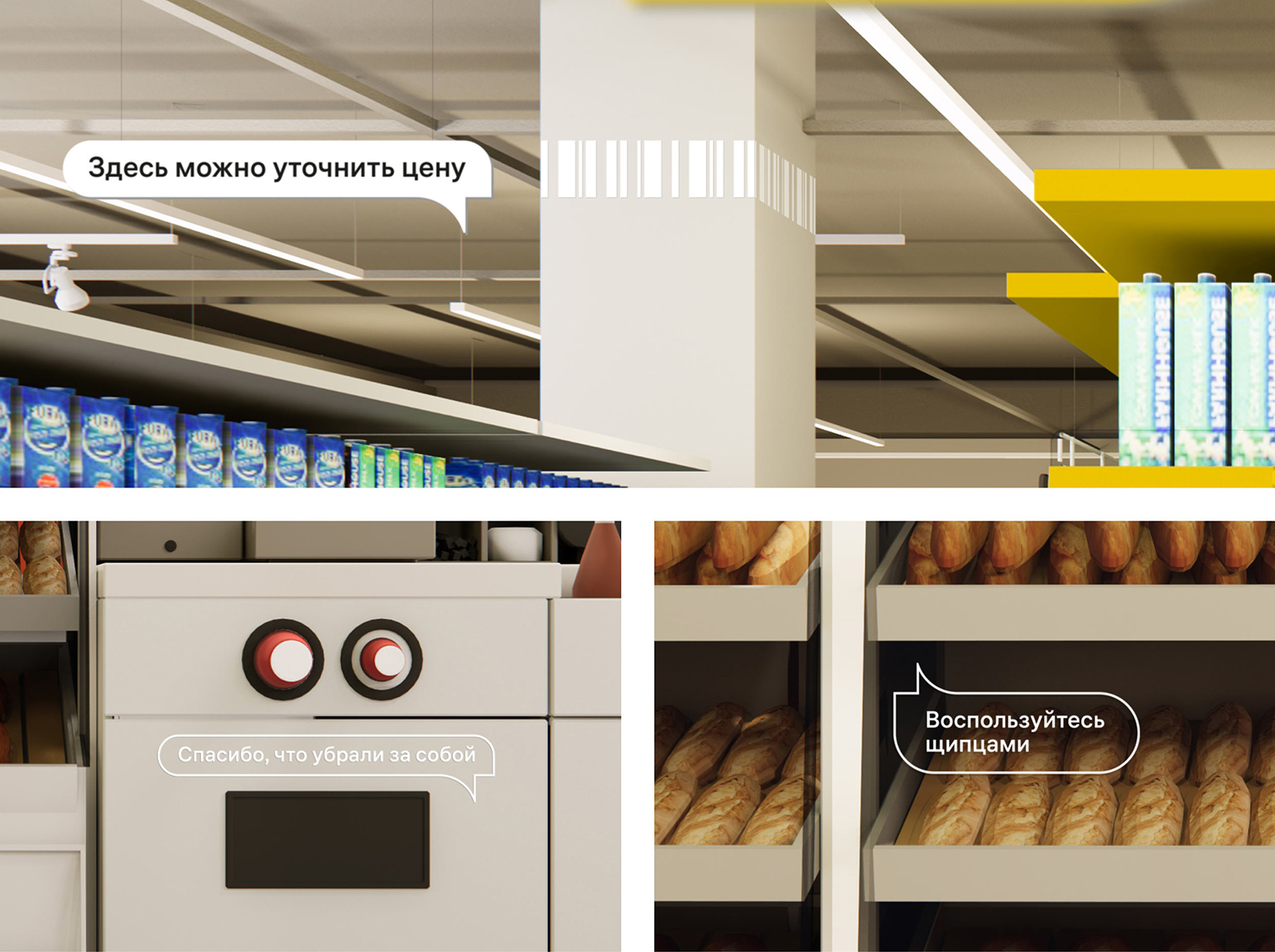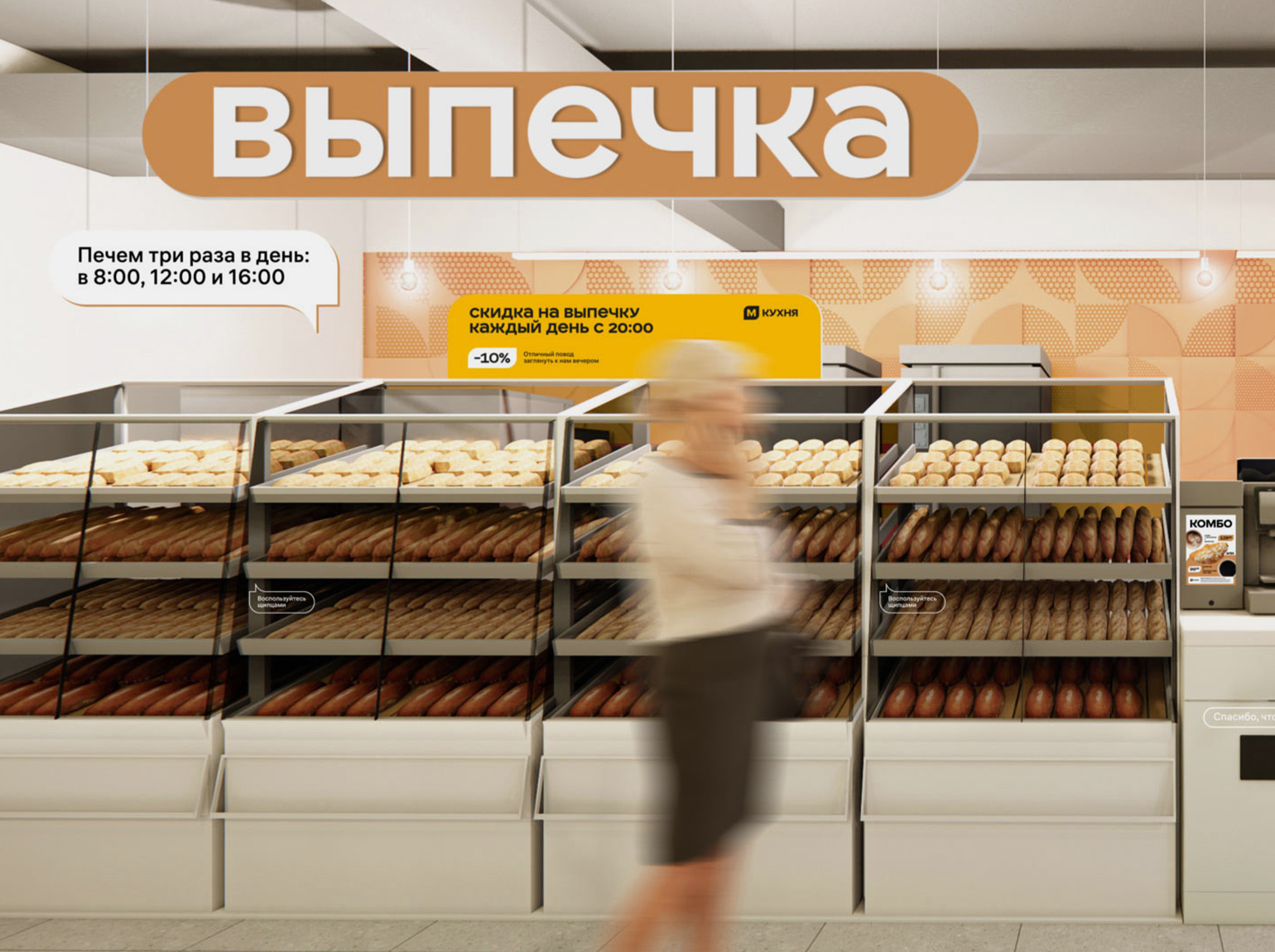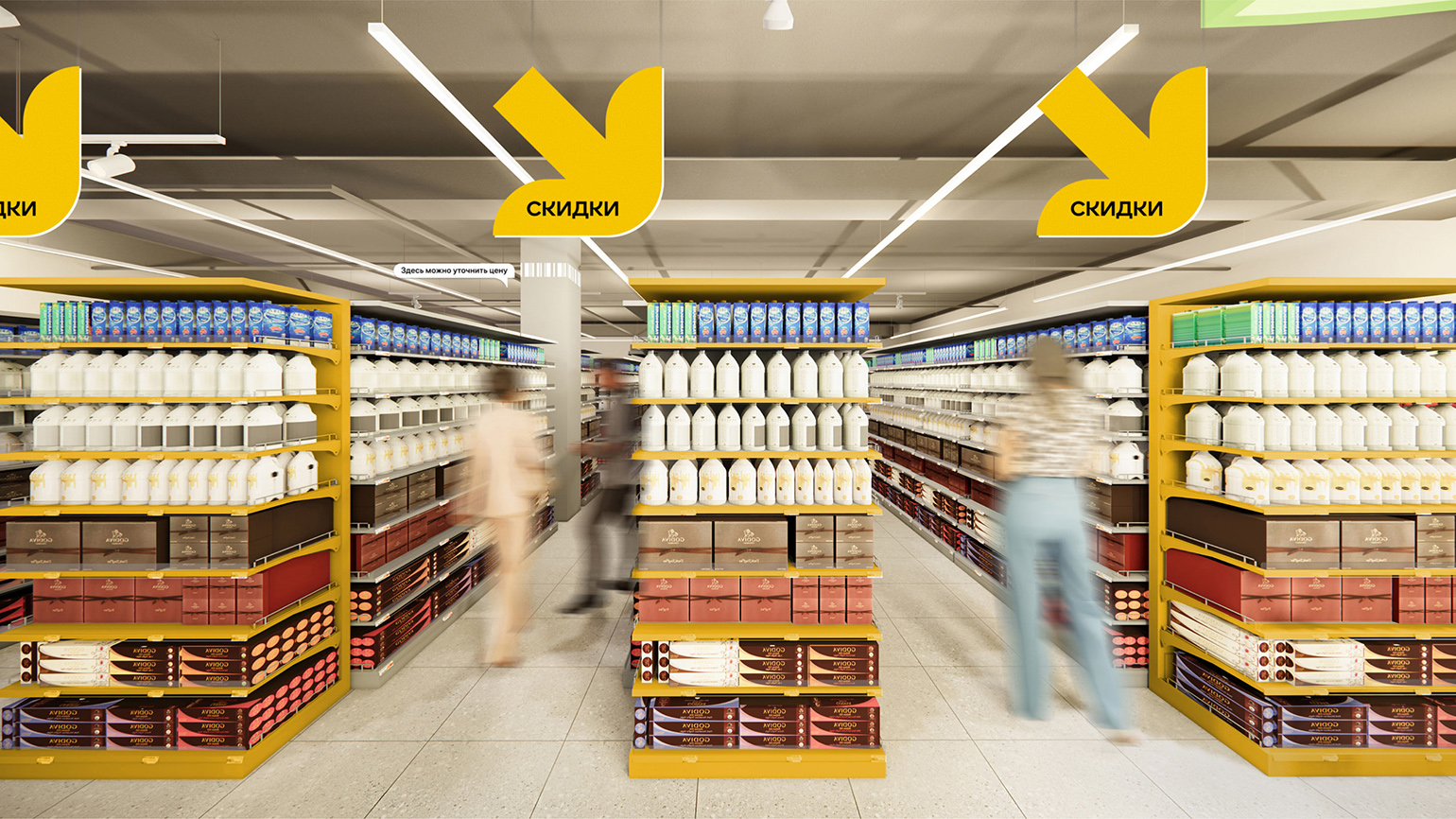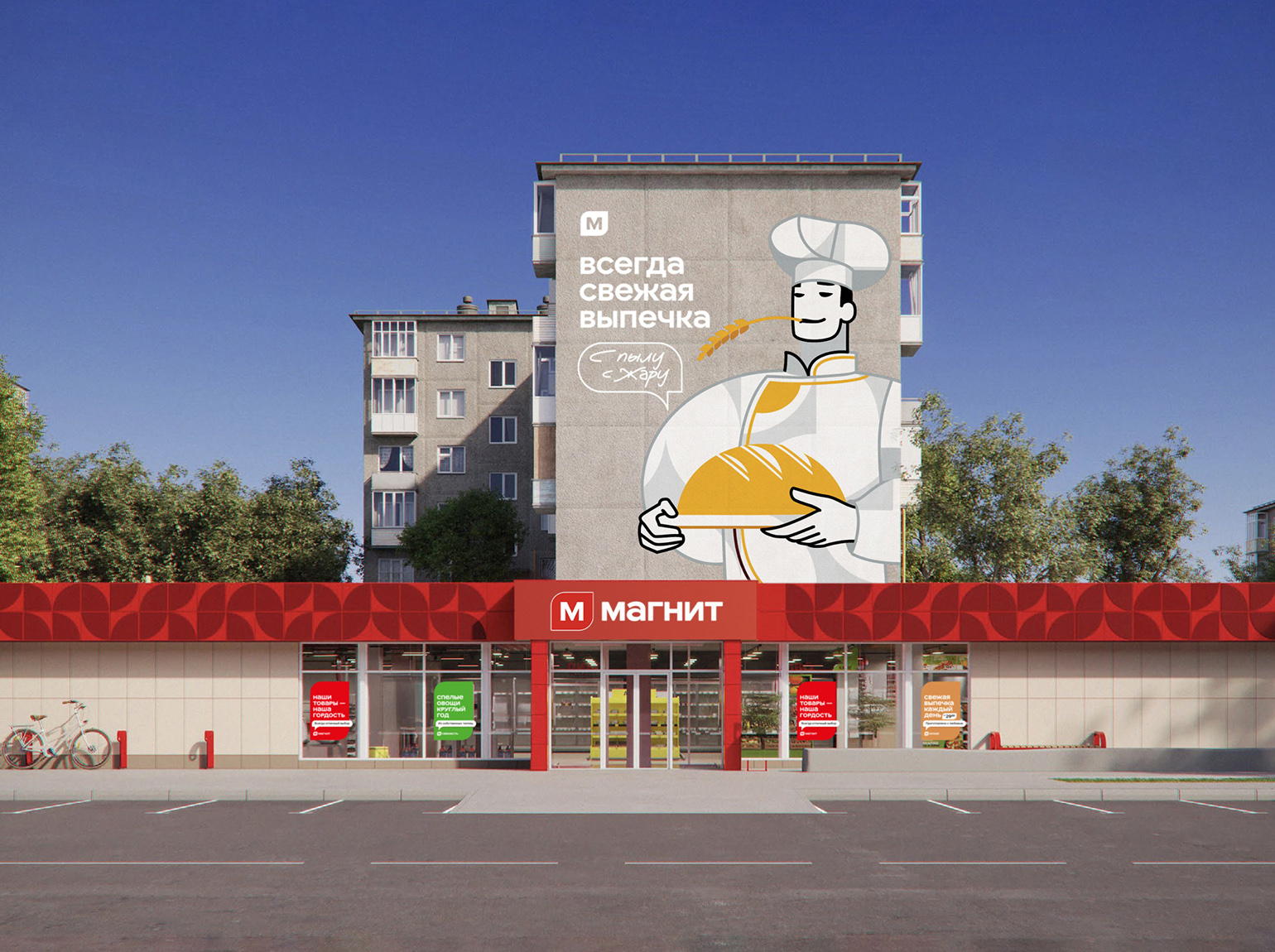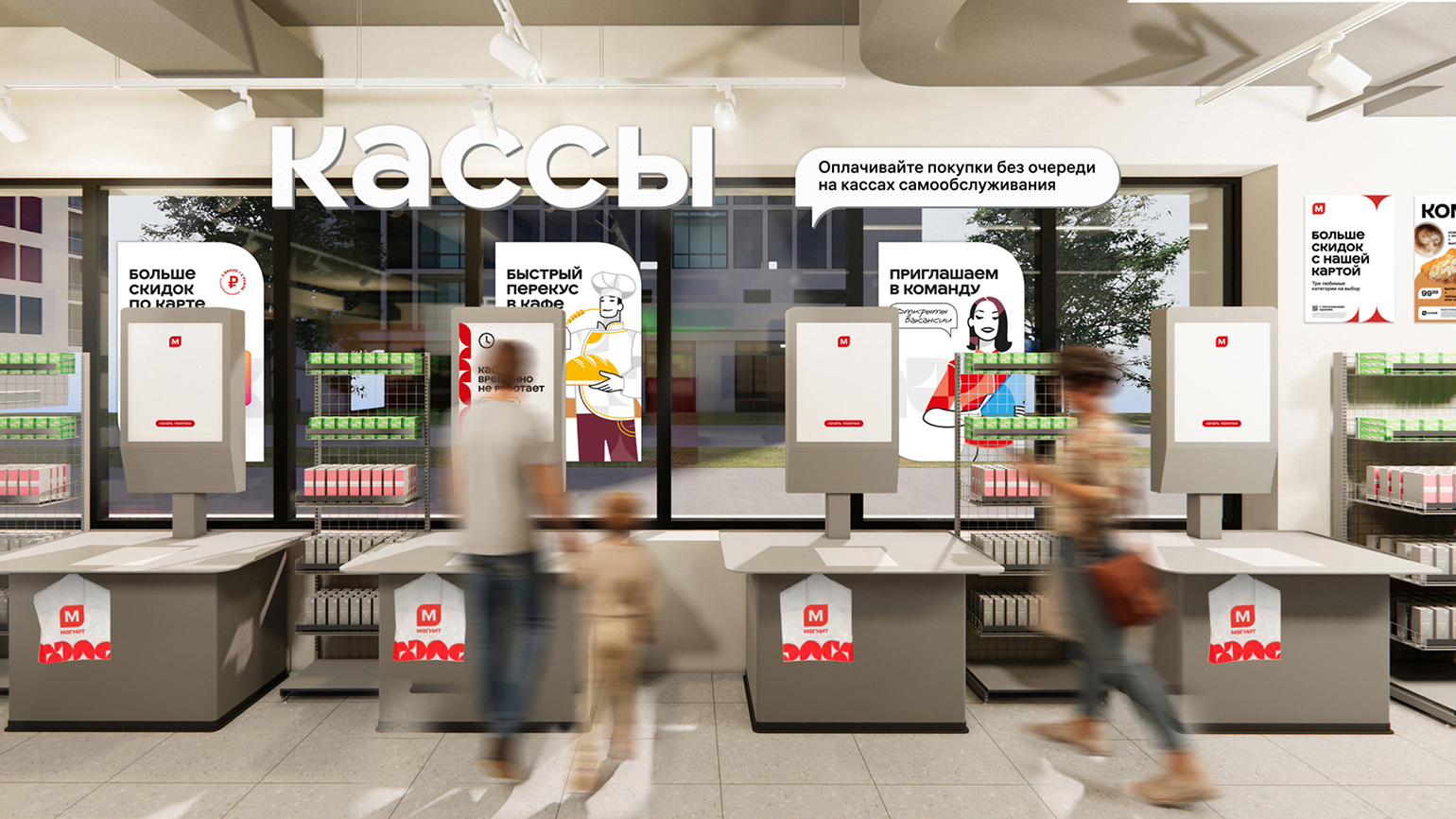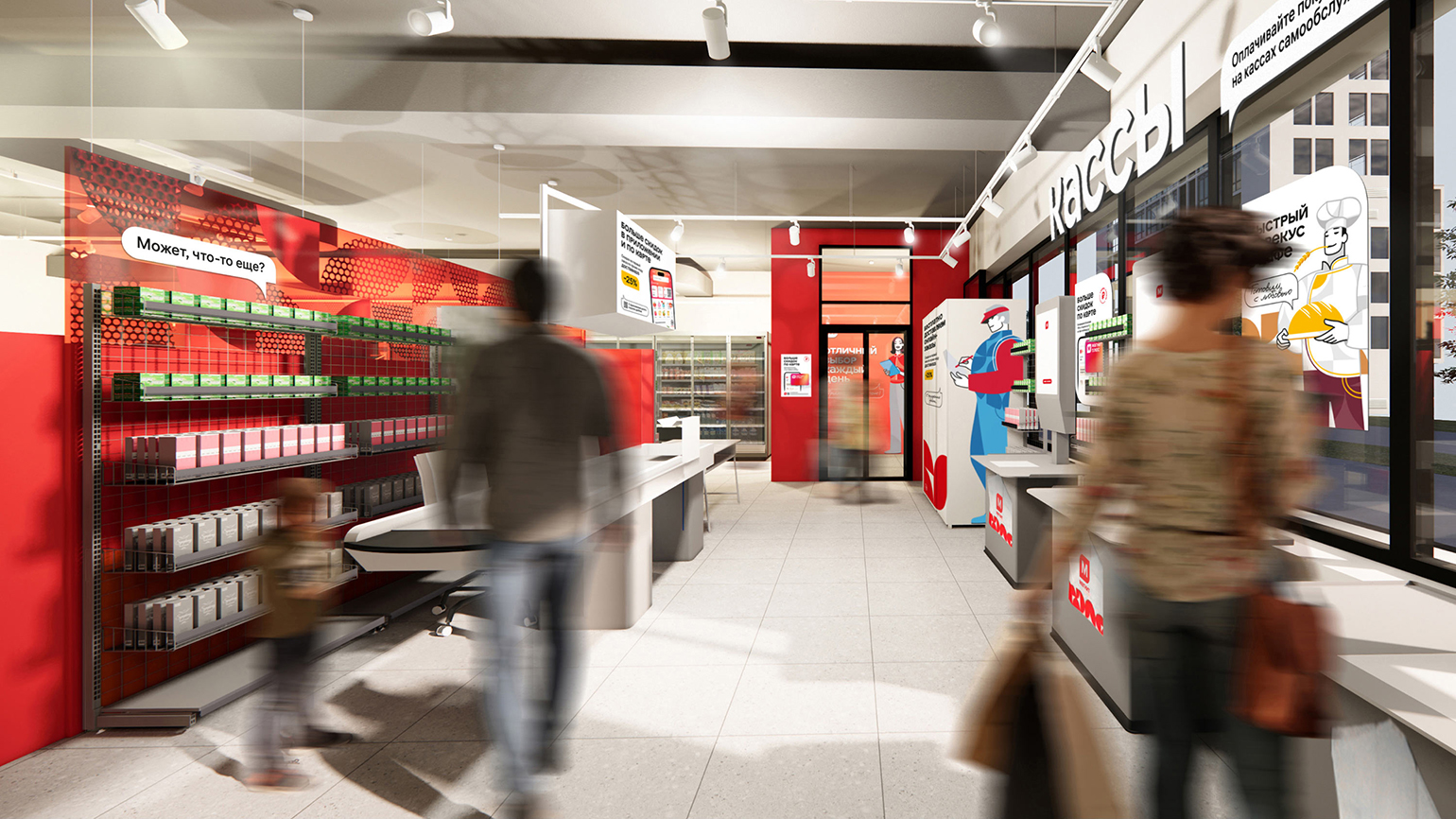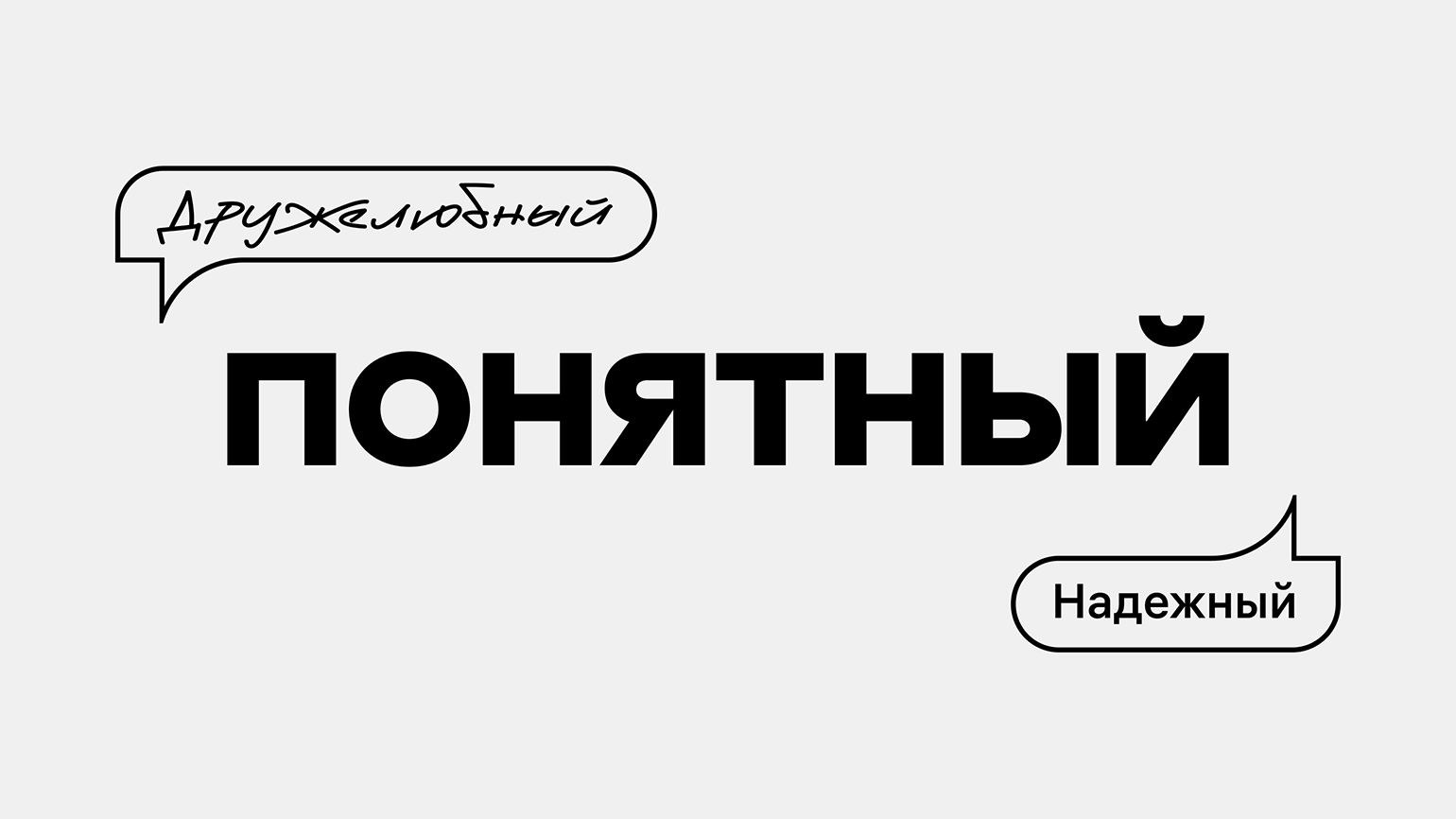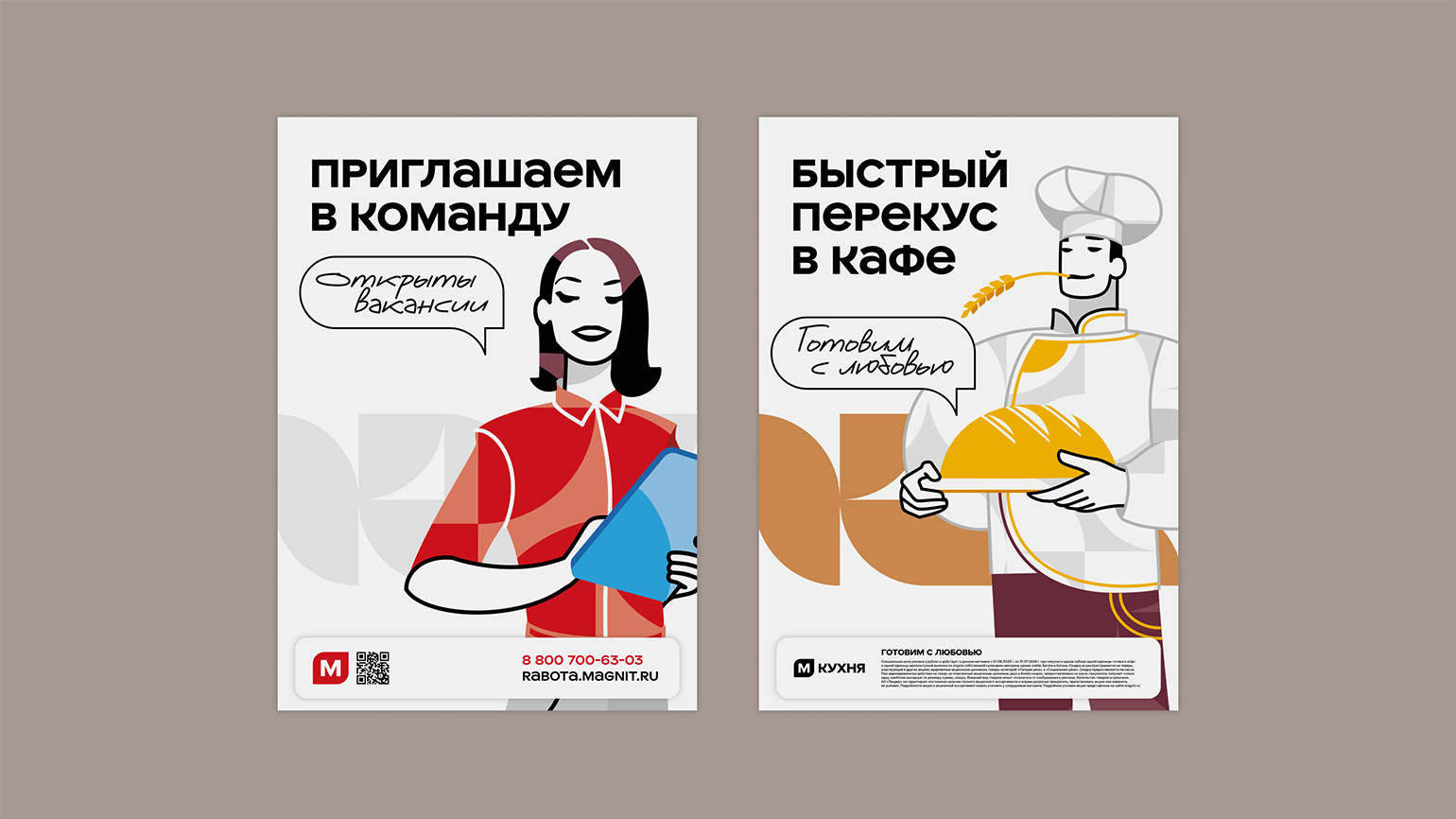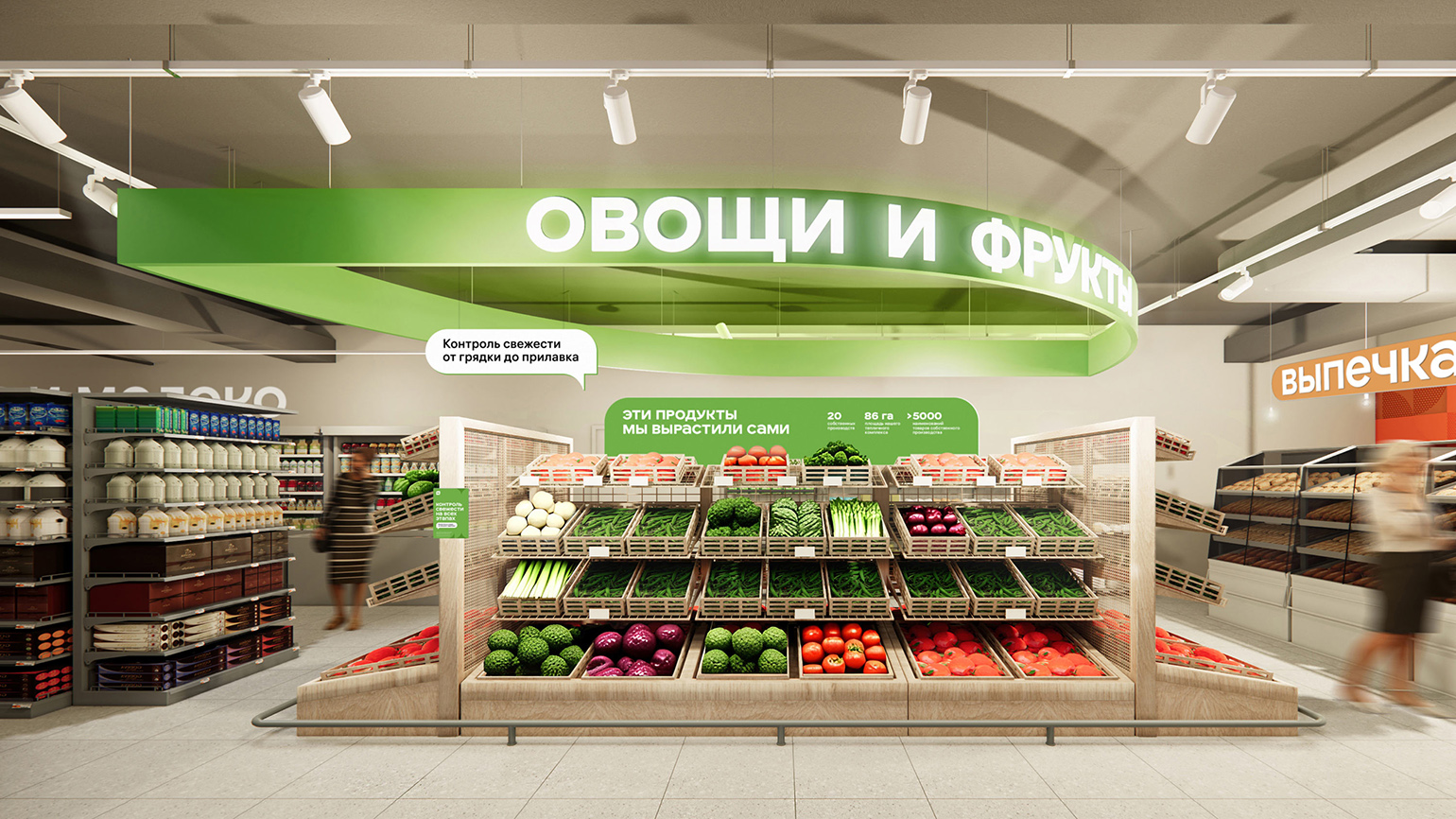
Логотип сети «Магнит» стал проще и понятнее, но сохранил узнаваемость. В новом знаке объединены буква М и фирменный лепесток, который символизирует природность и чистоту продуктов.
Для всей сети в студии разработали шрифт «Магнитус» — читабельный неогротеск с мягкими формами и деталями. Он работает как в навигации, так и на рекламных носителях, а мягкие округлые кириллические буквы передают открытость и «широту русской натуры». У прописных А и Е в шрифте необычное начертание для большей выразительности.
Учитывая широкую географию сети, в студии проработали буквы башкирского, татарского, чувашского, марийского, удмуртского и коми-зырянского алфавитов. Логотип и индивидуальный шрифт теперь используются на вывесках, в интерьерах, в навигации и в рекламе всех супермаркетов.
Кроме того, магазинам после реконцепции потребовались новые интерьеры, навигация и собственный визуальный язык общения с покупателями. В студии разработали зонирование, оформили пространства и подобрали мебель. В кафе и пекарнях появились перегородки с фирменным паттерном, которые перекликаются с контурами логотипа.
Зону овощей и фруктов выделили яркой вывеской, в контуре которой угадывается символ «Магнита».
В навигации добавили бабблы с подсказками — они рассказывают о преимуществах сети. Внимание к акциям привлекают подвесы-стрелки и тематические вывески.
Указатели на полках оформлены с использованием паттерна, рифмующегося с шрифтом и цветовой системой бренда.
Для визуальной коммуникации в студии придумали фирменных героев — «мастера», «пекаря» и «руководителя». Они появляются на постерах и элементах навигации. Новой визуальной системой будут пользоваться дизайнеры, архитекторы, проектировщики и руководители магазинов.